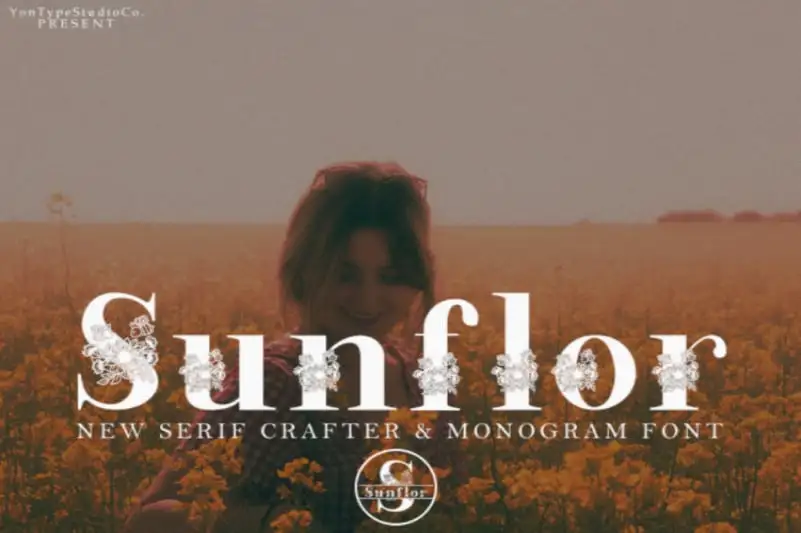
Sunflor Display Font – Download Grátis
Sunflor Display Font é uma elegante tipografia serifada perfeita para estilos visuais naturais e românticos. Suas linhas sutilmente arredondadas tornam-a ideal não apenas para logos relacionados à natureza, mas também para agradáveis convites de casamento, projetos impressos, anúncios e até mesmo editoriais nas revistas e jornais. A Sunflor Display é uma fonte que convida o usuário a explorar designs cheios de vida, personalidade e harmonia, tanto na web quanto em impressões tradicionais. Suas características elegantes se combinam perfeitamente com um estilo gráfico refinado, tornando-a uma escolha ótima para criações impecáveis em qualquer projeto visual.